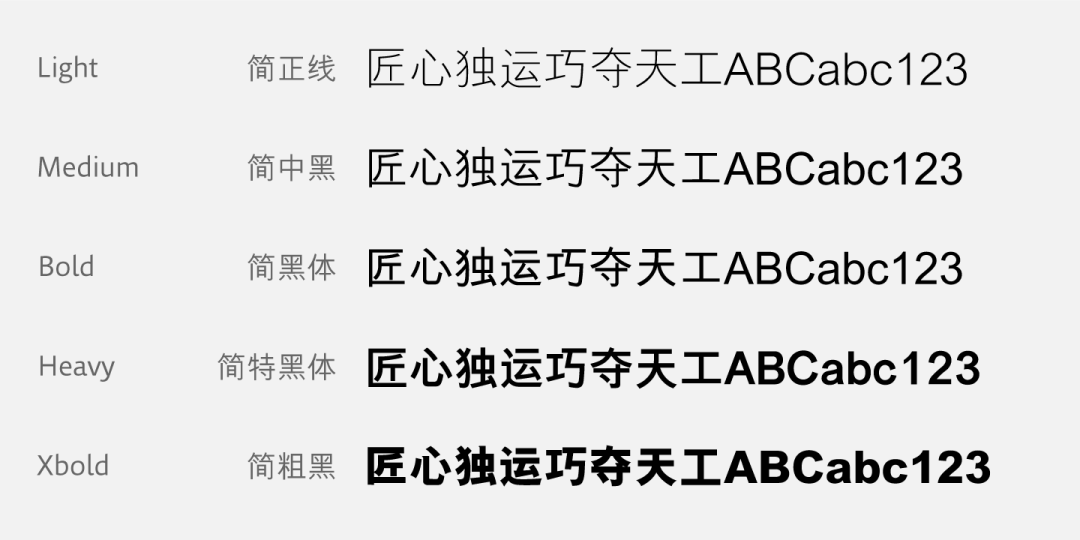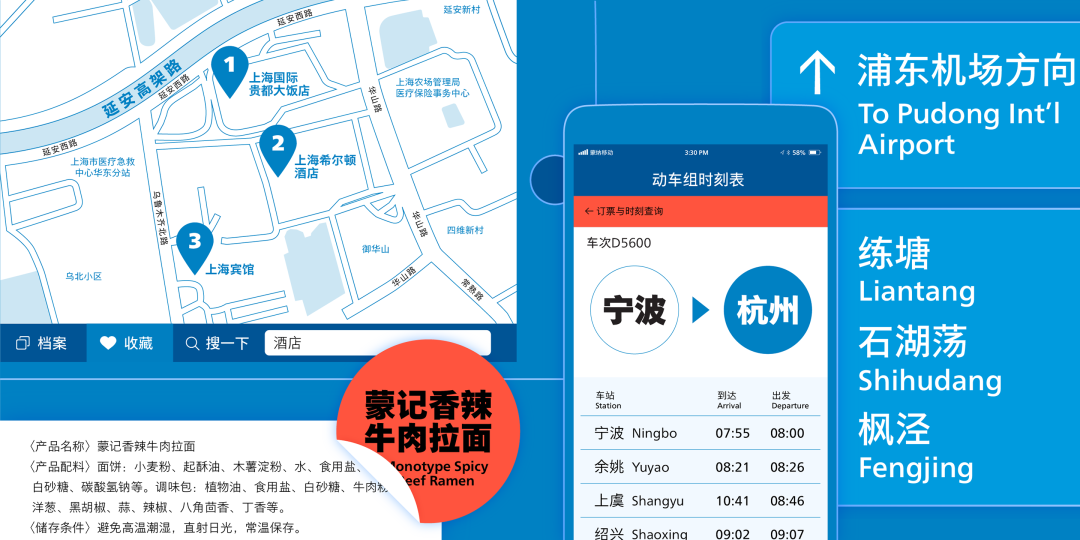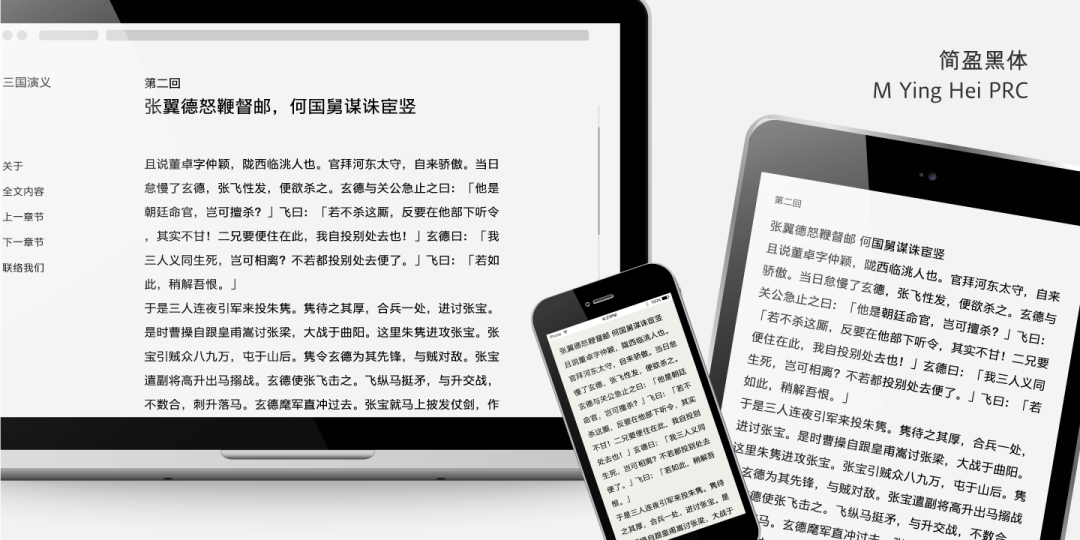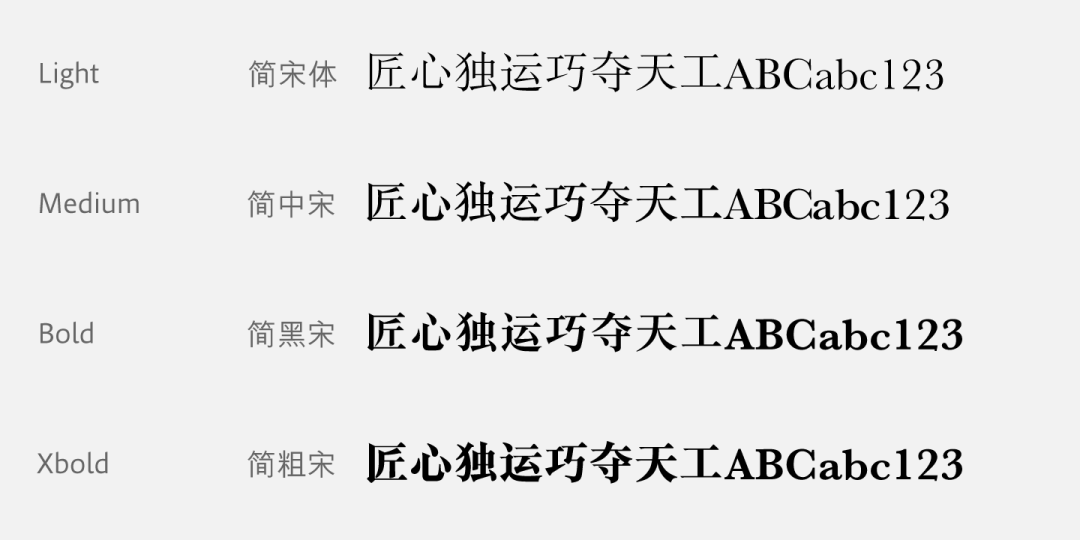
蒙纳五款中文字体通过强制性国家标准 GB18303-2022
导读:8 月 1 日,强制性国家标准 GB18030-2022 《信息技术中文编码字符集》正式实施。蒙纳旗下盈黑等五款经典中文字体作品首批通过 GB18030-2022 符合性测试,将在广度和深度上更为适配企业用字需求。
关于 GB18030-2022
强制性国家标准 GB18030-2022《信息技术中文编码字符集》由国家标准化管理委员会于 2022 年 7 月 19 日发布,并于 2023 年 8 月 1 日正式实施。
作为中文信息技术领域最重要的基础性标准,GB18030-2022 对汉字和我国少数民族文字进行了统一编码,进一步完善我国中文信息处理交换的需要。
GB18030-2022 与上一版标准相比,涵盖了更多生僻汉字,基本满足人名、地名生僻字以及古籍、科技等专业领域用字的各类需求,从而提升语言文字规范化、标准化和信息化水平。
蒙纳字体作品获首批认证
标准发布后,为秉持提供优质中文字体产品及服务的理念,蒙纳团队协同合作,增补完善现有字体作品。
8 月,蒙纳旗下五款广受欢迎的经典中文字体,首批通过 GB18030-2022 符合性测试(Level 2),包括蒙纳盈黑、蒙纳翔鹤黑体、蒙纳黑体、蒙纳宋体与蒙纳中线黑体。
> 蒙纳盈黑    MYingHei
盈黑由蒙纳经验丰富的字体设计师许大鹏和长期合作伙伴郭炳权设计制作,是应中文无衬线体在屏幕及印刷上表现更佳、更为现代优雅的要求而推出的。
它具备五款字重,拥有更为宽大的中宫,使其既观感清晰友好,又在屏幕和印刷上具备极佳的易读性。此外,蒙纳盈黑还能够与多款经典西文字体和谐匹配,如 Neue Helvetica®、Neue Frutiger®、Avenir® Next、Univers® Next 等。
> 蒙纳翔鹤黑体    MXiangHe Hei
翔鹤黑体由小林章领衔设计,设计标准源于其对应的日文字体 Tazugane。翔鹤黑体作为一款极具人文感的字体,是蒙纳英文字体 Neue Frutiger 的完美匹配。在延续 Neue Frutiger 特征的同时,翔鹤黑体的诸多细节考量还使得中英文混排在视觉上更趋和谐。
亲切、自然、优雅、甚至高级感,皆为翔鹤黑体的关键词,也让其轻松驾驭广泛的设计用途与场景,为设计注入情感,让文字的传达更具人情味。
> 蒙纳黑体    MHei
作为一款骨架内缩的黑体,蒙纳黑体仍然保留了传统书法的曲线,使其识别性非常高。除了传统的骨架及细节,蒙纳黑体也不失现代感,因而得到许多商业公司的青睐,从前香港机场内的空间导示、旅游简介、报章杂志等随处可见它的身影。
> 蒙纳宋体    MSung
蒙纳宋体的设计灵感源于上海印刷研究所在 1960 年开发的铅字模。它骨架略为内缩,笔画粗细对比明显,起笔、收笔、转折处有着醒目的设计细节,因而具备传统意蕴。除大尺寸字号外,蒙纳宋体也适合杂志出版等长篇内容排版,传达出硬朗与轻快并存的感觉。
蒙纳中线黑体    NewSansMT
蒙纳中线黑体诞生已二十年,为初代电子产品字体显示而生。通过简化框架与减少装饰,从而在保持清晰易读、极简中性的基础上,大大节省储存空间,在屏幕上有较为理想的表现。
结语
这五款经典字体作品随着增补完善,信息处理和技术支持能力也将得到拓展,覆盖更为广泛的用字需要,适配更为专精的行业需求。